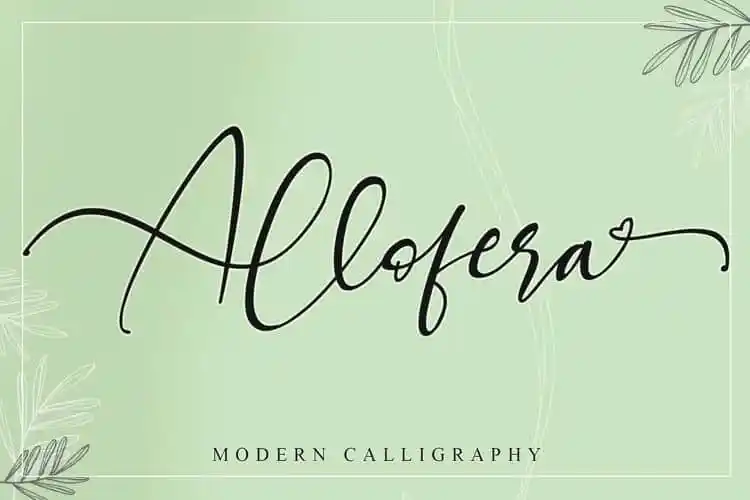
Allofera Calligraphy Font – Download Grátis
A Allofera Calligraphy Font é uma nova tipografia de escritura feita à mão, que traz um toque fresco e moderno ao seu design. Combinada a sua forma elegante e versátil como script, esta fonte perfeita para postais de casamento. Oferecida por Stefani Letter, é ideal tanto para trabalhos DIY quanto para o uso em redes sociais como Instagram, transformando qualquer ideia criativa num verdadeiro trabalho de arte. Seja para adicionar um toque delicado a cartas de casamento ou para dar um ar romântico às suas postagens do dia-a-dia, a Allofera Calligraphy Font é uma escolha imperdível para quem busca uma fonte única e moderna que destaca seu estilo pessoal.